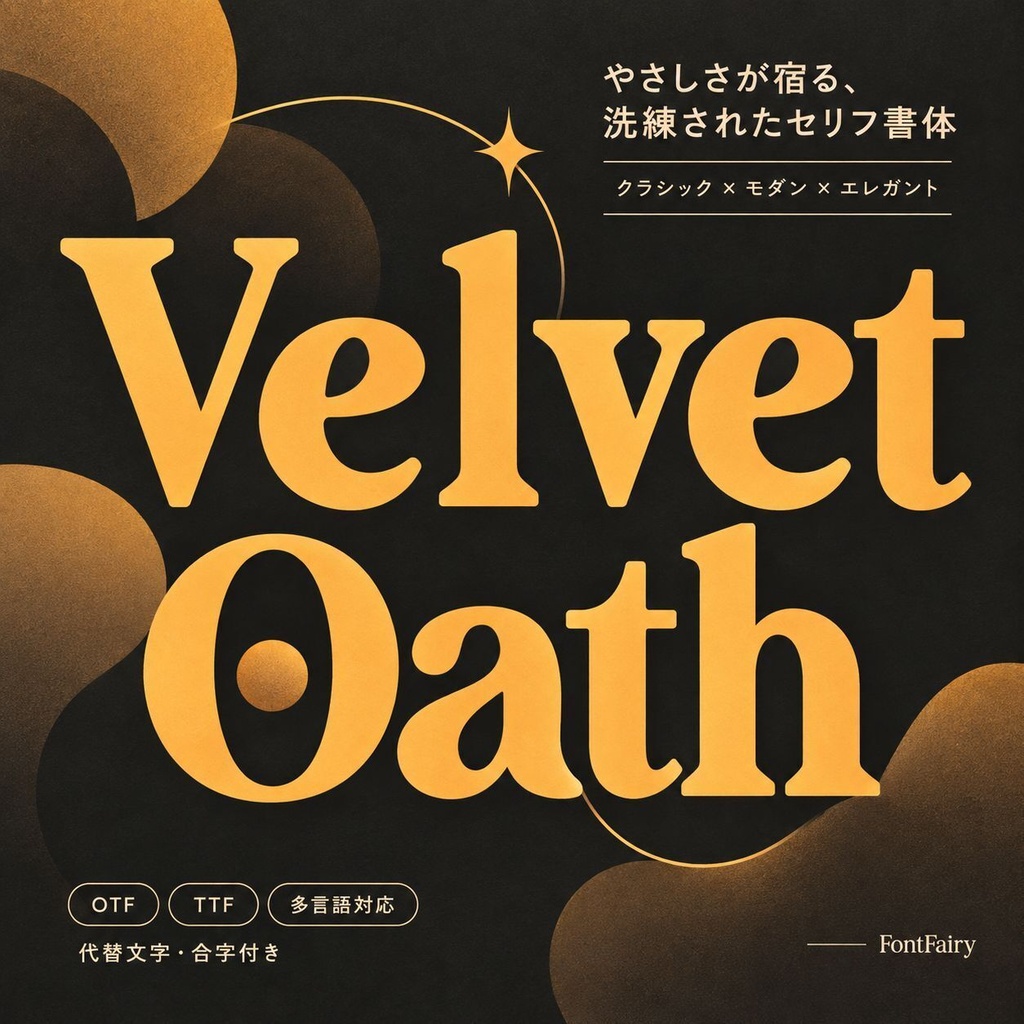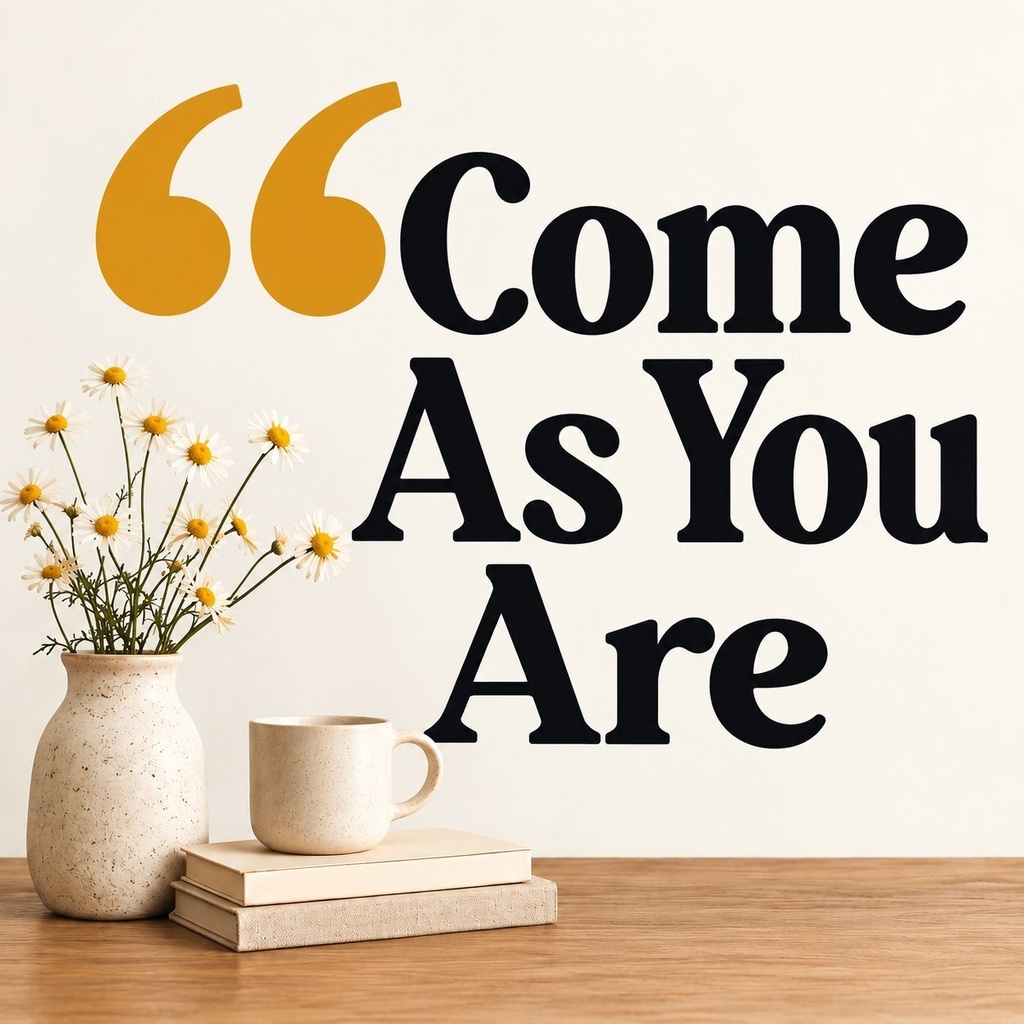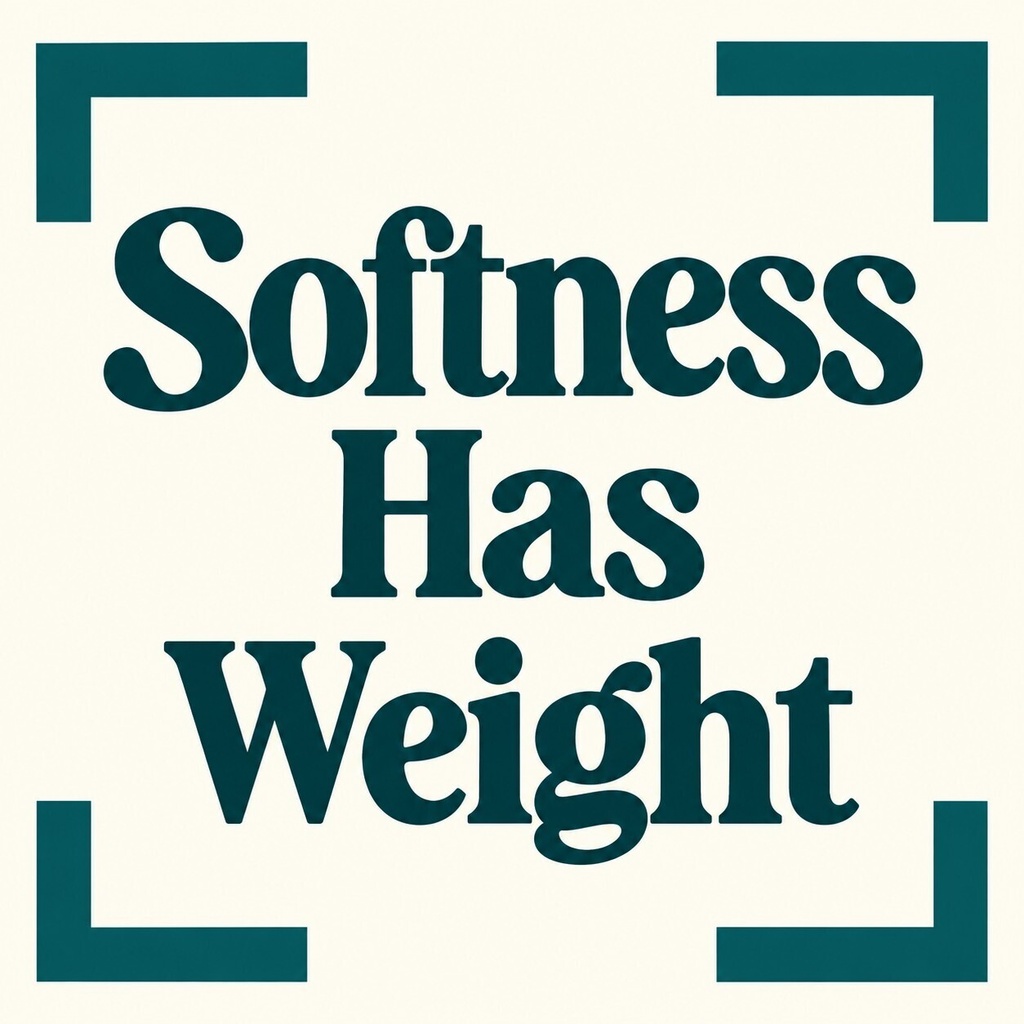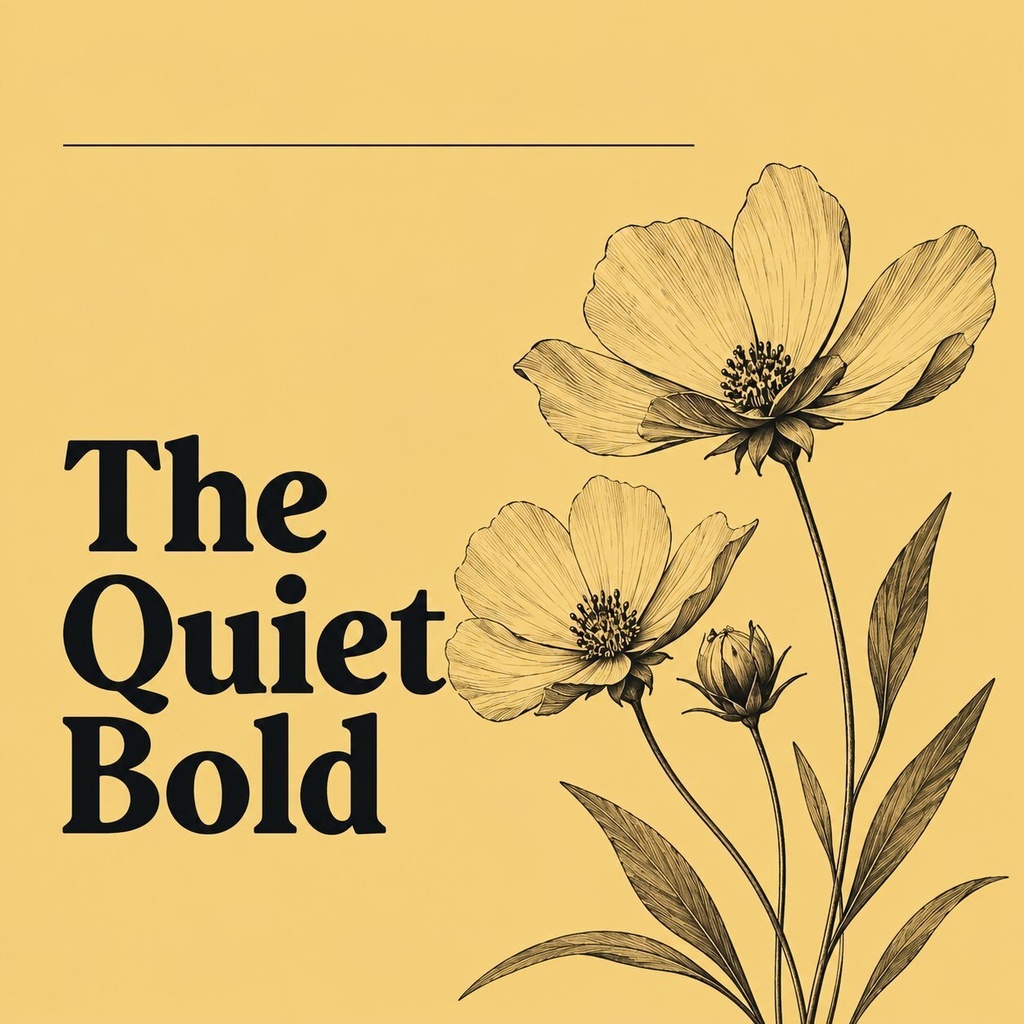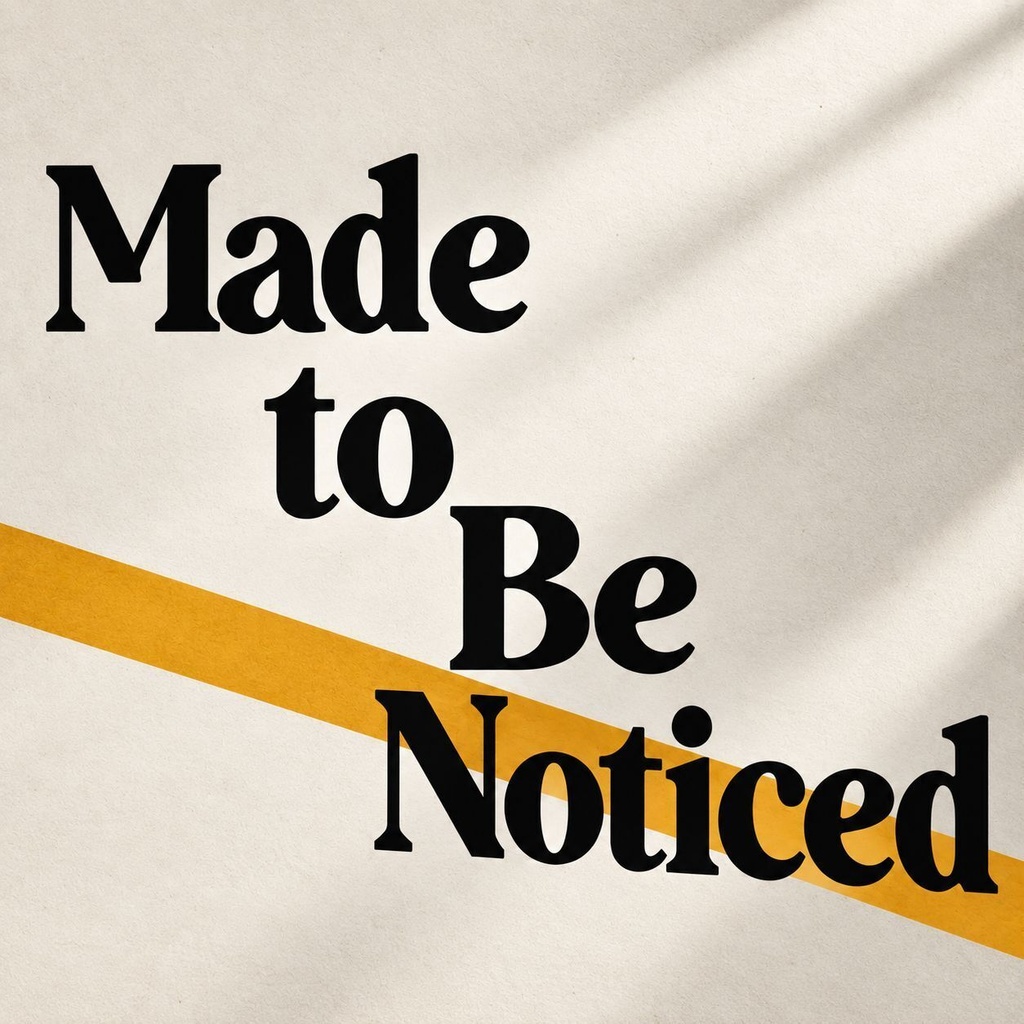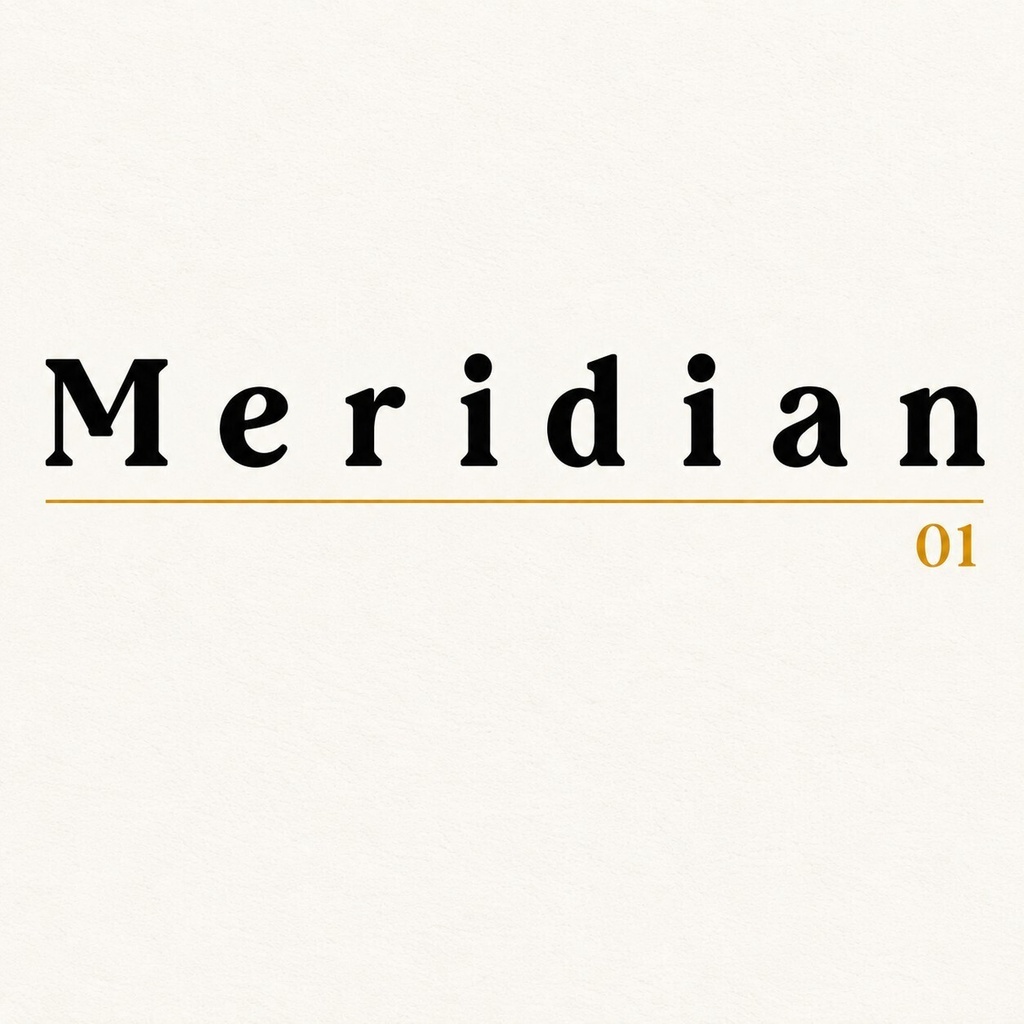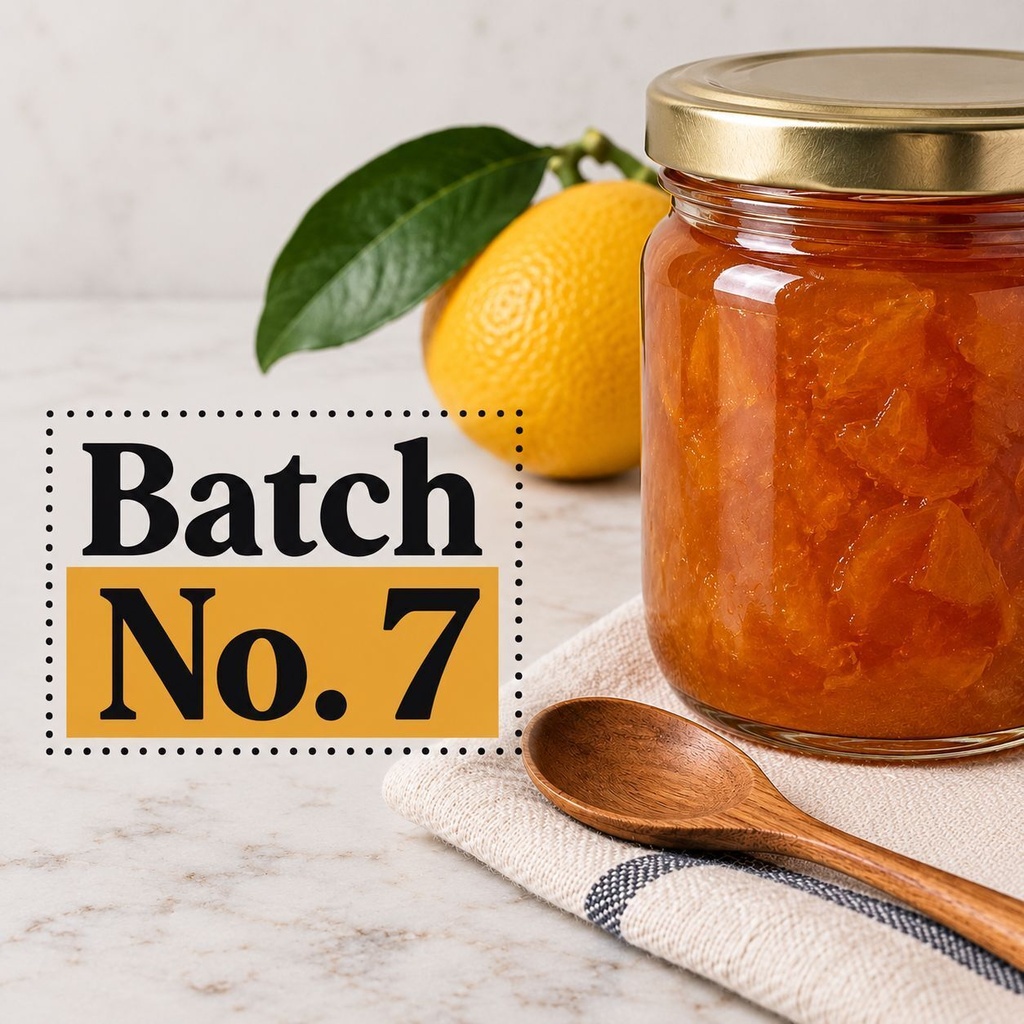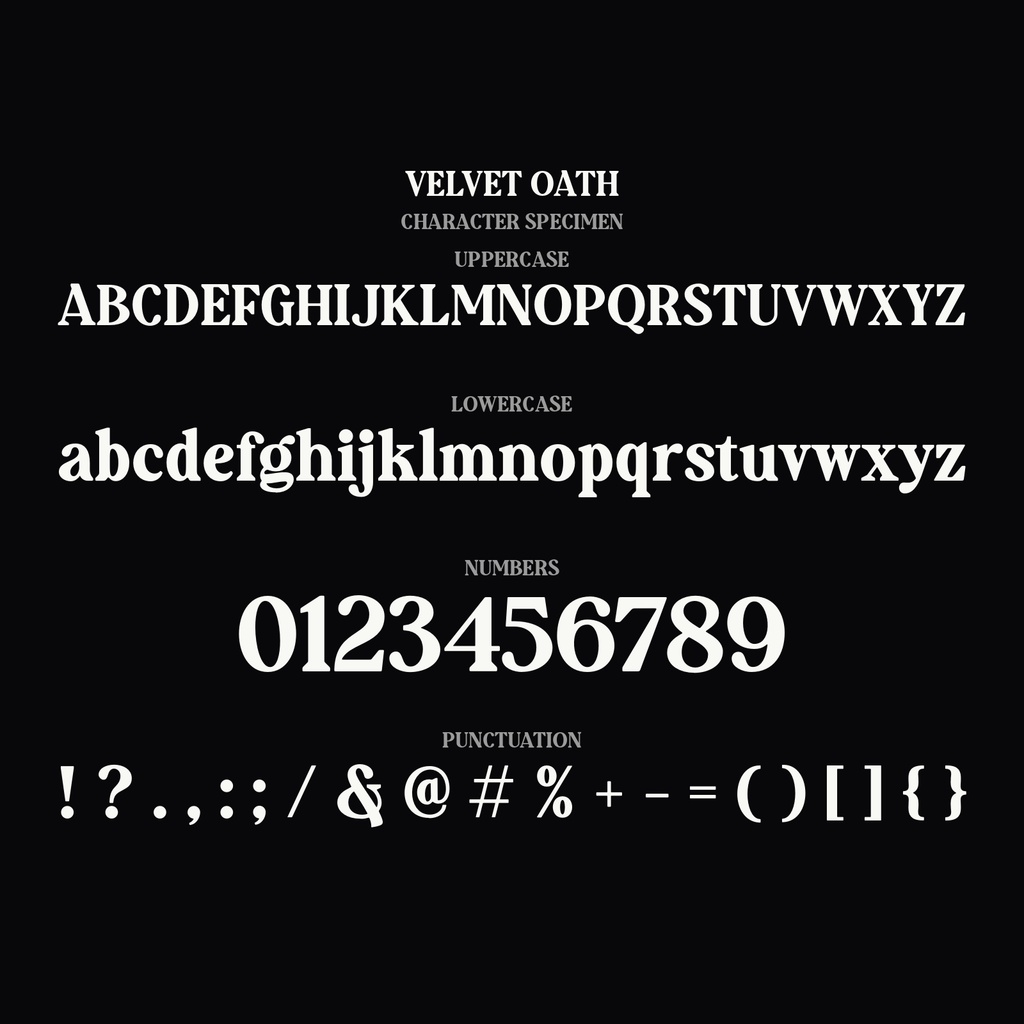
Velvet Oath | セリフ欧文フォント | ロゴ・ウェディング向け 商用利用可能
リガチャとディセンダントで彩る、重厚で柔らかなセリフ欧文フォント。 Velvet Oathは、太めのボディにソフトな丸みを纏ったモダンセリフで、ロゴ・ブランディング・ウェディング・ポスターなど、洗練された印象が求められる場面に最適です。リガチャと各文字のオルタネイトを搭載し、タイポグラフィに個性と流れるような表情を与えます。 収録内容:大文字・小文字、数字・記号、多言語対応、リガチャ(合字)、各文字のオルタネイト、PUAエンコード、特殊記号「✦」(A+でアクセス) 対応文字:ラテン文字(アルファベット)中心の欧文フォントです。日本語・キリル文字・ギリシャ文字は収録されていません。 用途:ロゴ・ブランディング、見出し、ポスター、ウェディング招待状、アルバムジャケット、パッケージ、同人誌、グッズ、配信素材、テロップ、サムネイルなど、大胆でありながら上品なタイポグラフィが求められる作品全般。 形式:OTF / TTF / WOFF / WOFF2 対応環境:クリスタ、イラレ、アドビソフト、Procreate、Canva、ワード、パワポなど、OpenTypeフォントに対応するアプリケーション全般。PUAエンコード対応のため、キャラクターマップがあれば全キャラクターにアクセス可能です。